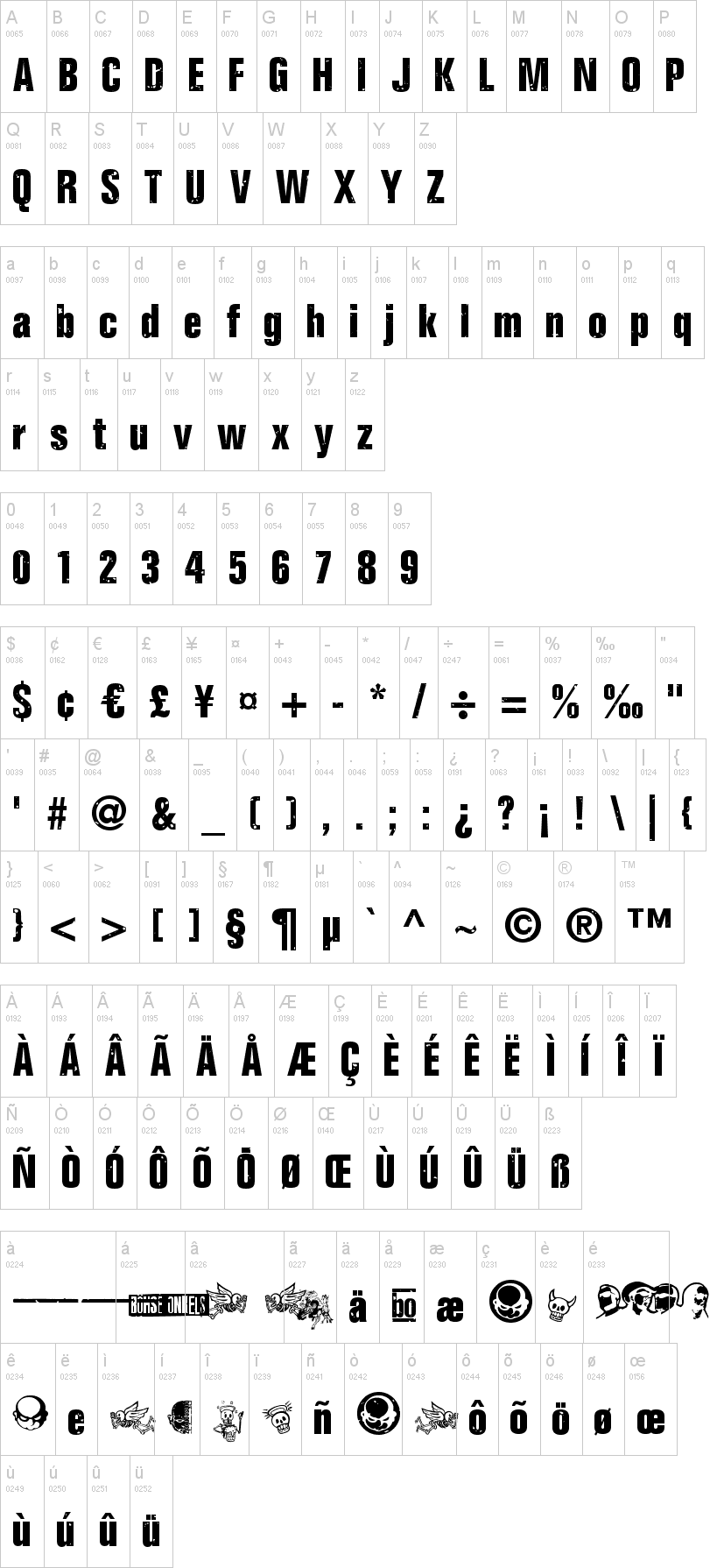
Шрифт Onkelz 2014
"ONKELZ 2014" ist die Fan-Schriftart der deutschen Rockband "Böhse Onkelz".
"ONKELZ 2014" is a fan-font of the german rockband "Böhse Onkelz".